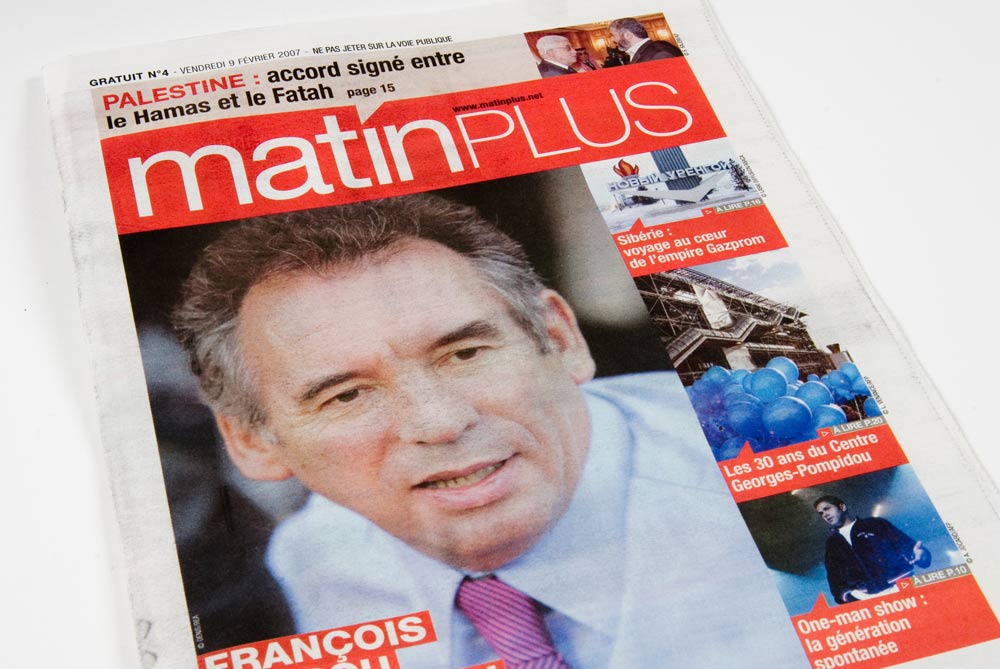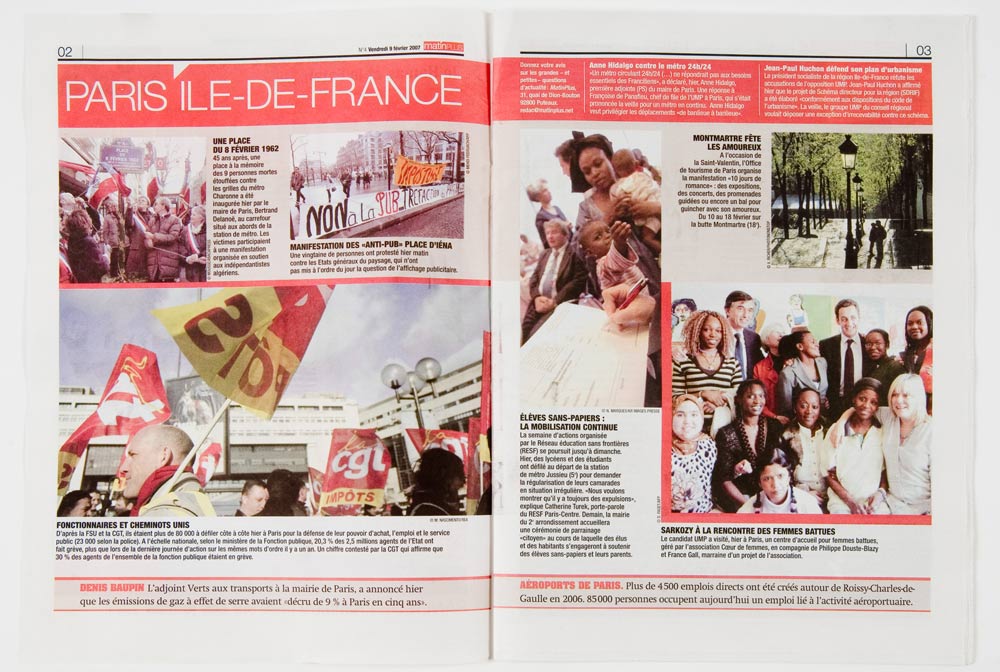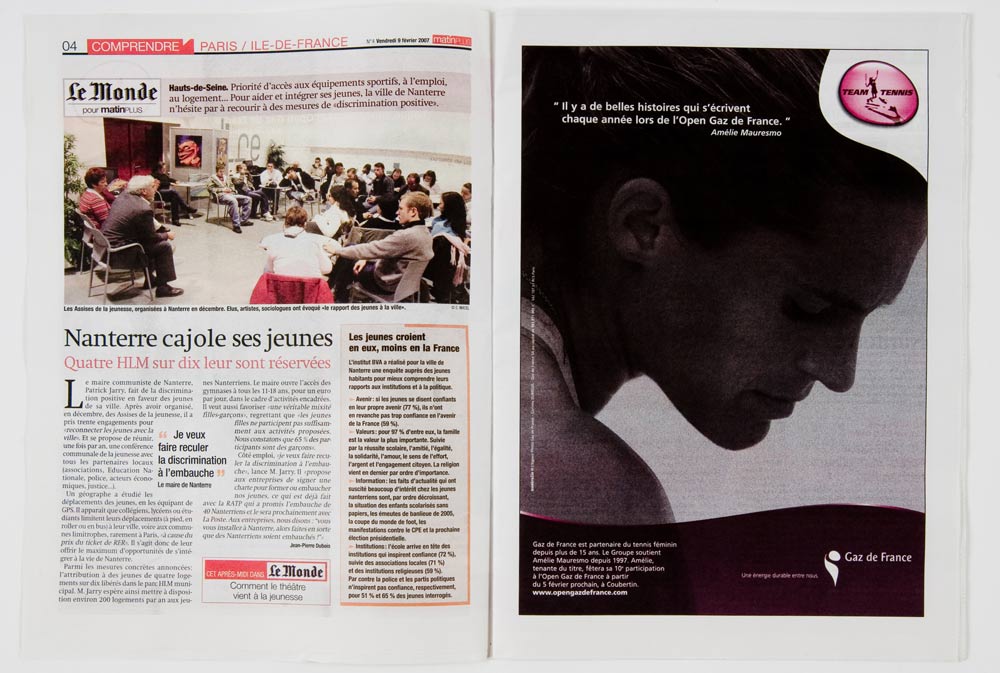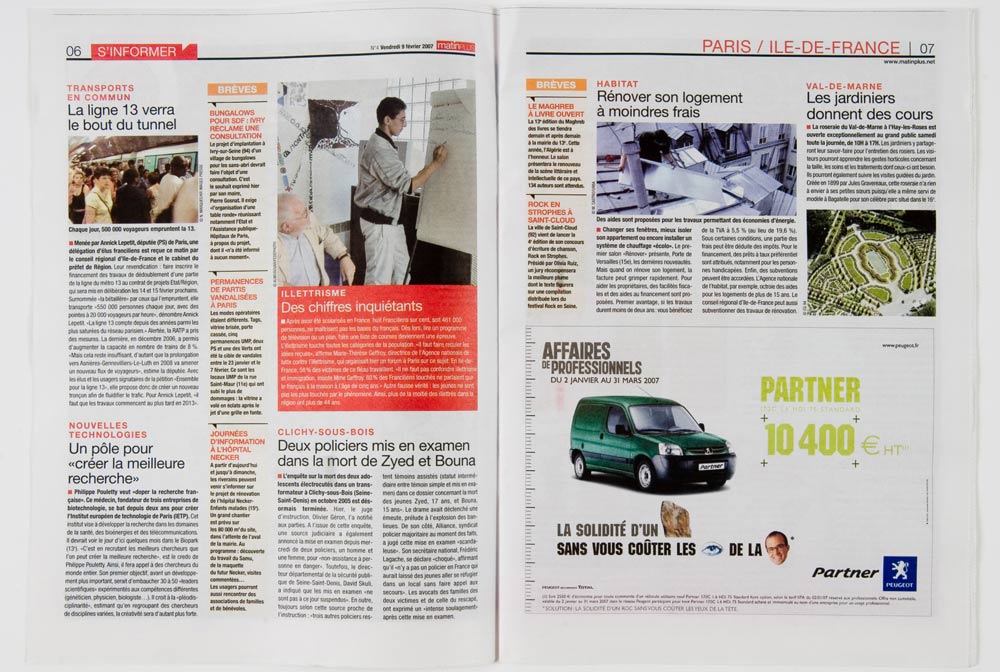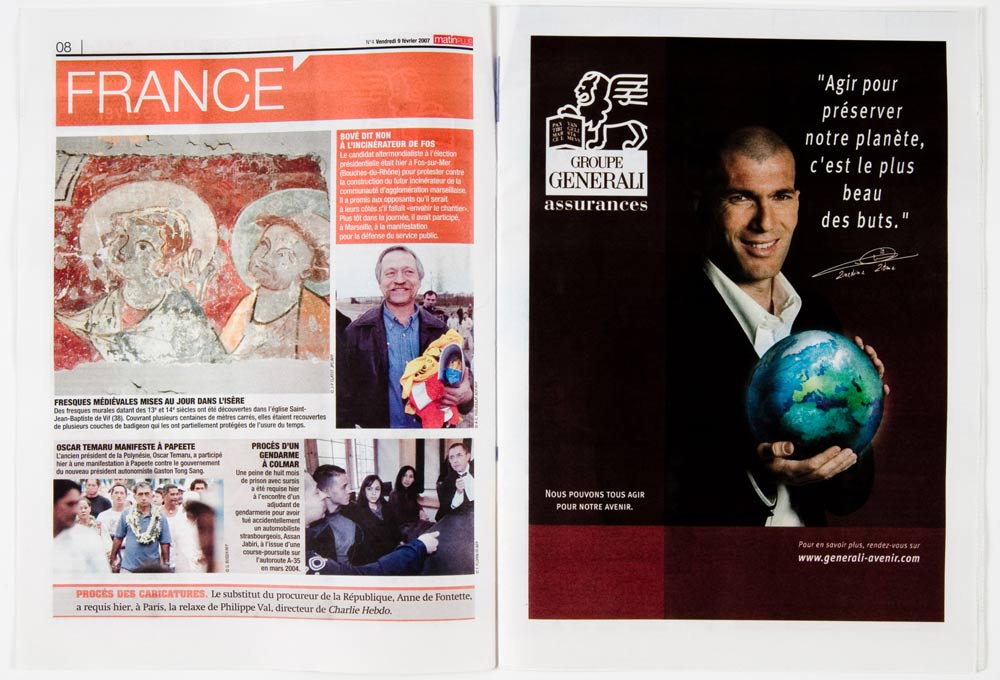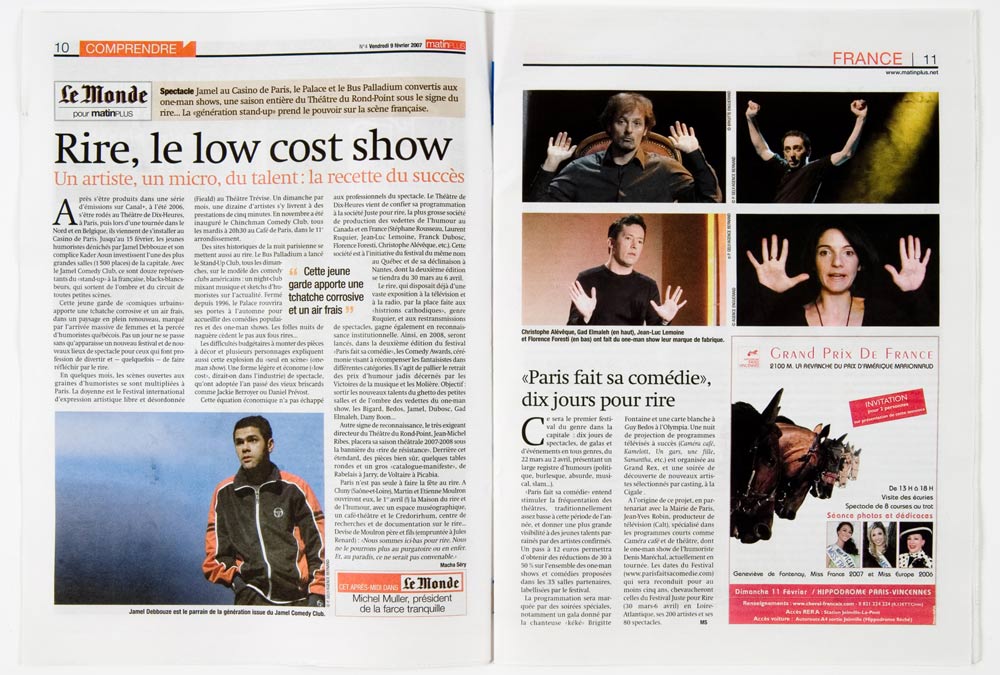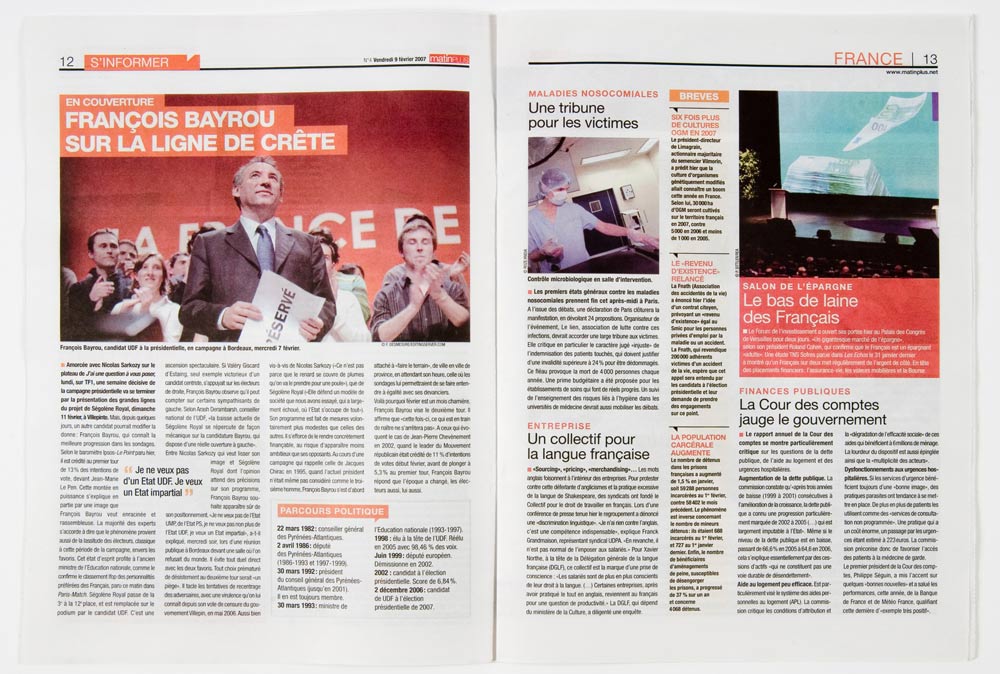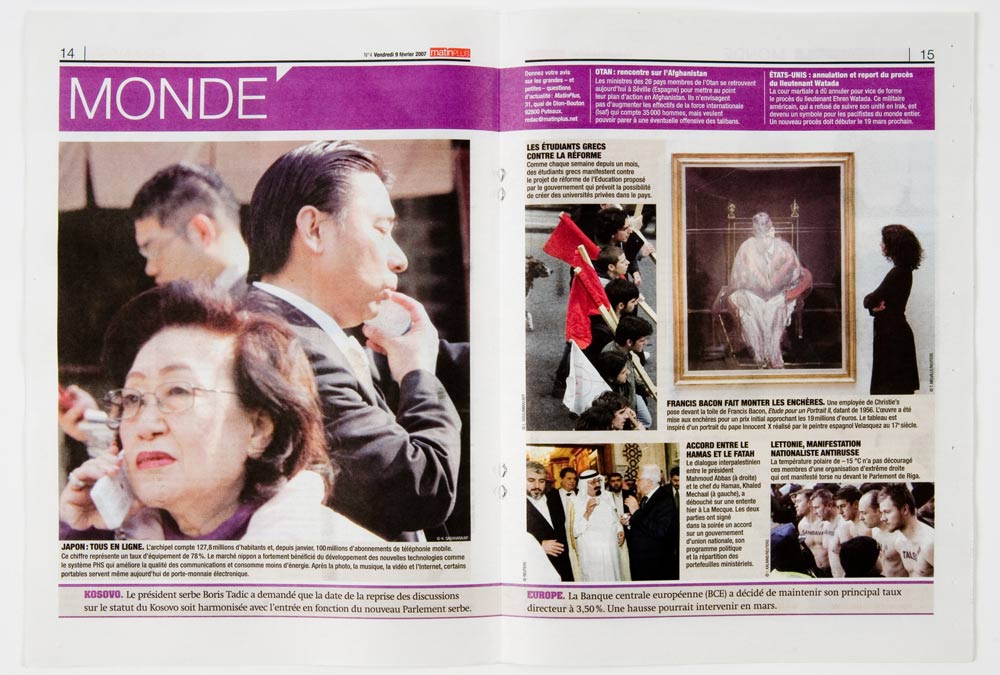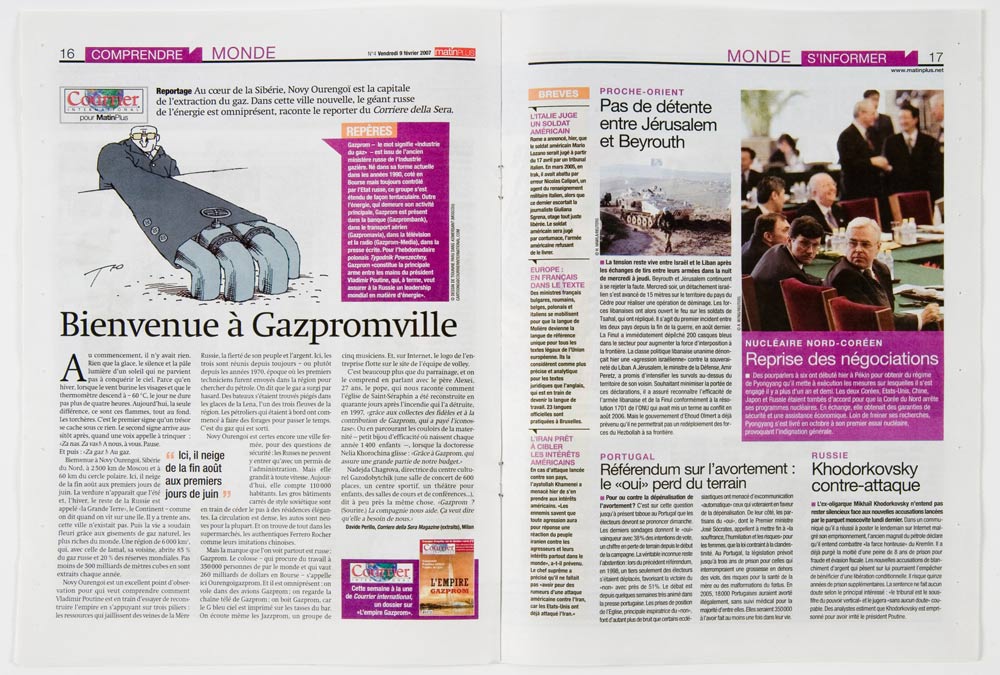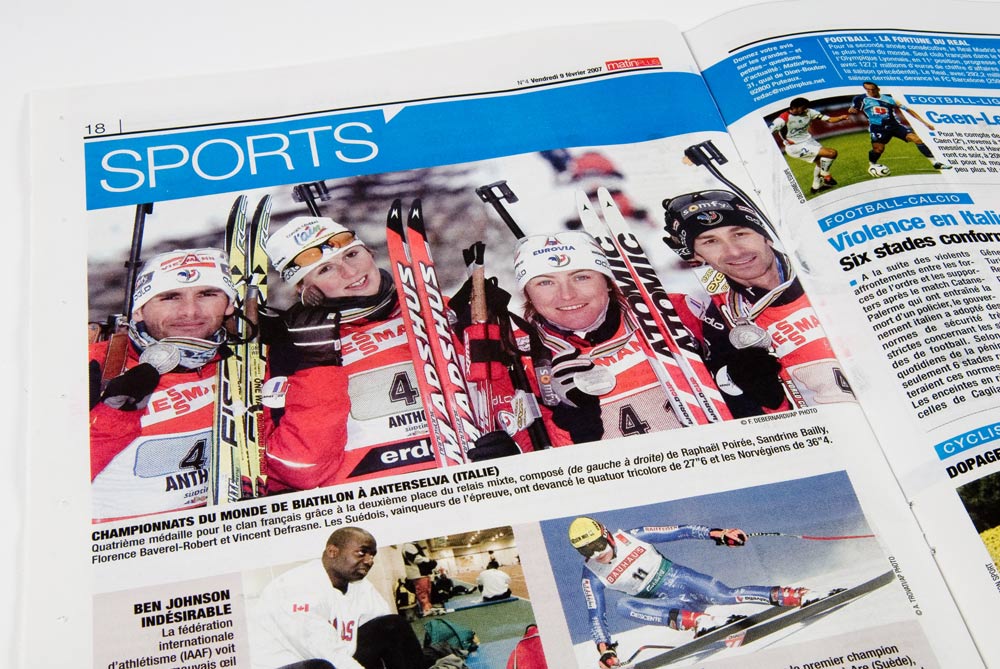
Thèmes forts: «moi je suis fils de Lubalin…», «on peut presque parler du son qui émane d’une typographie…», «…une Marque, devrait exiger une typo spacifique de ses agences…». «Delpire a créé une typo exclusive pour Citroën…», «la campagne pour Carrefour… pourquoi payer plus cher ce qui n’est qu’une Marque… typo dépouillée, populaire… le Franklin», «le net oblige d’aller encore plus vers des codes visuel… le net est en train de tuer la typo…», «le numérique est en train de tuer la culture…», «Les Anglo-saxons sont beaucoup plus rigoureux sur le respect de leurs codes graphiques… maîtres du Print…», «sortie de crise de la Presse, la stratégie du Monde pour les dix ans à venir…», «…une image vaut mille mots disait Mao Tze Tung…», «Le poids des mots et le choc des photos… Roger Thérond…», «le gratuit du soir, un access au prime time de la soirée…»…
On ne peut que constater l’extraordinaire vitalité de Jacques Séguéla, même si parfois il s’emmèle les pinceaux (la chronologie des habillages de télé) et présente le net comme une monde sans sensualité… on peut ne pas être d’accord ;-) mais dans l’ensemble il semble maîtriser plutôt bien les sujets qu’il aborde nous donnant une vision du futur de la Presse plutôt optimiste. La sortie de crise est au bout d’un tunnel qui fut déjà stigmatisé par Jean Gabin dans un film de Denis de la Pattelière pendant les années 50. Je vous laisse deviner le film dont il s’agit. Les trois premières bonnes réponses recevront un grand salut chaleureux de design et typo ;-)
La mise en page de Matin Plus est assurée par les services artistiques du journal Le Monde en lui conférant une rigueur et une qualité de layout digne des meilleurs quotidiens payants. Preuve s’il en faut que le gratuit n’est pas condamné à délivrer un design de «chiottes» au prétexte que tout le monde s’en fout.